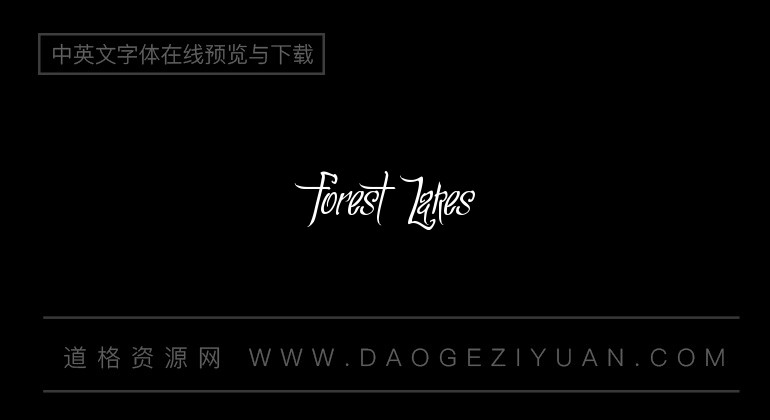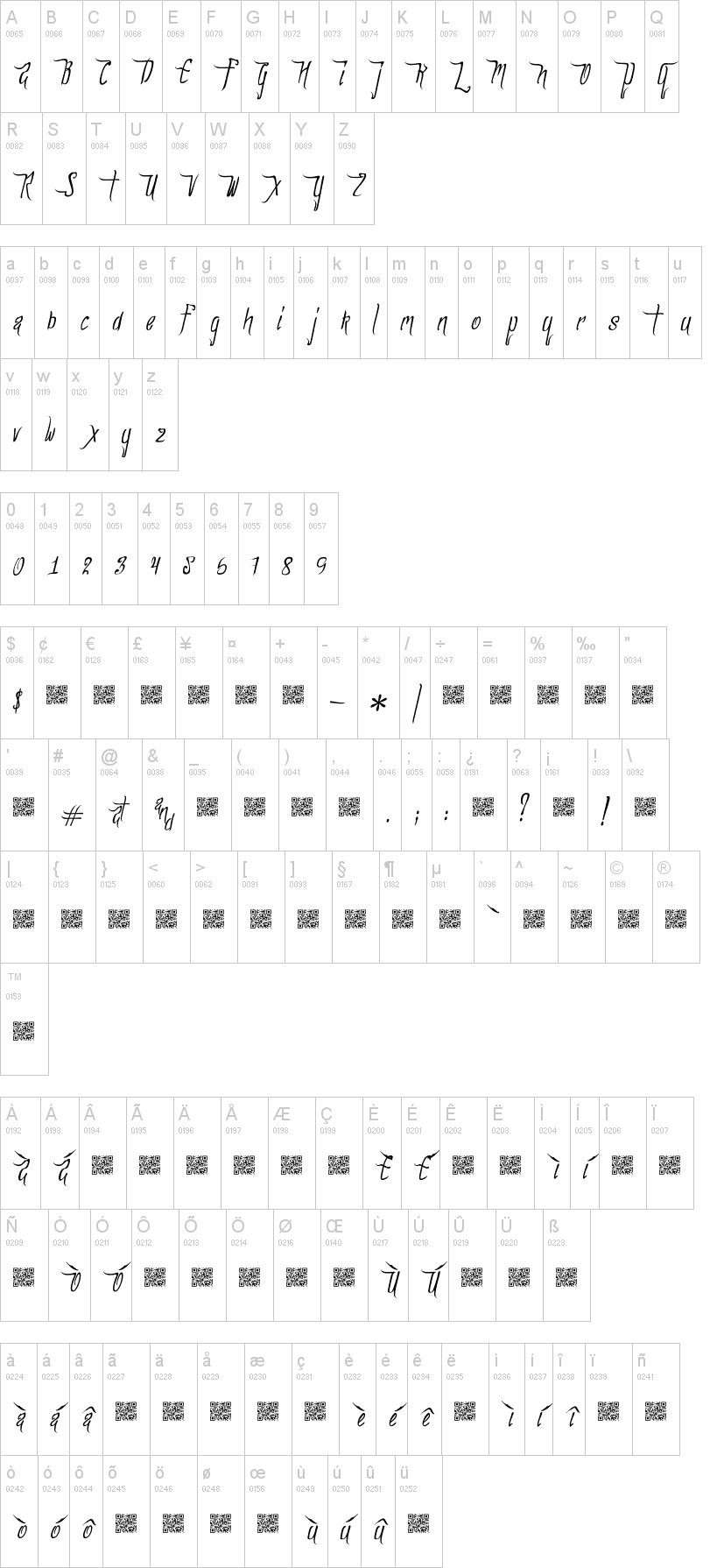
Forest Lakes是一款简洁而又鲜明的字体,它的字体风格融合了现代感和传统感,让文字看起来更加有质感。该字体具有较强的可读性,能够清晰地传达文字的意思,而且字体的粗细也让文字看起来更加舒服。它的特点是字母之间的间距较大,让文字看起来更加清晰而且不显得拥挤。内容介绍
Forest Lakes是一款非常不错的手写艺术字体,具有很好的视觉感,适合于文化类的宣传设计、商业类品牌的广告和产品包装设计以及个性化文字排版等较多场景。